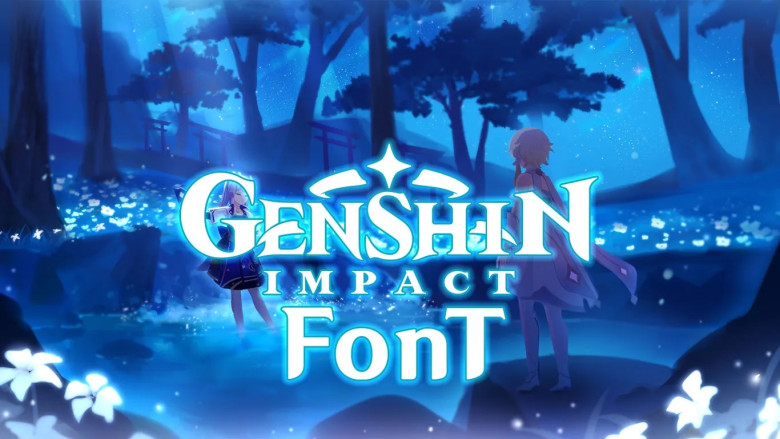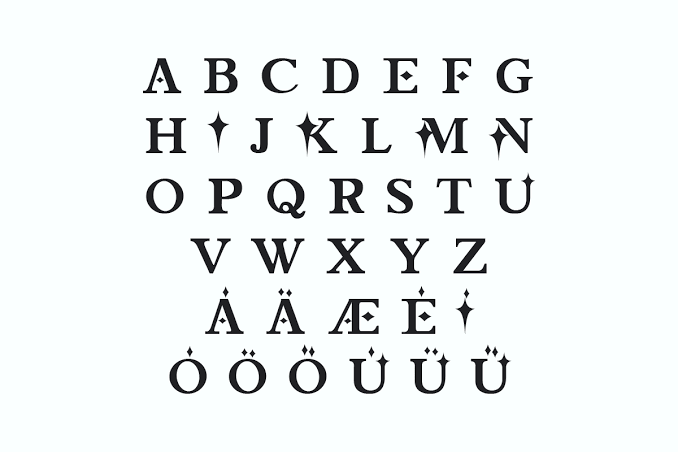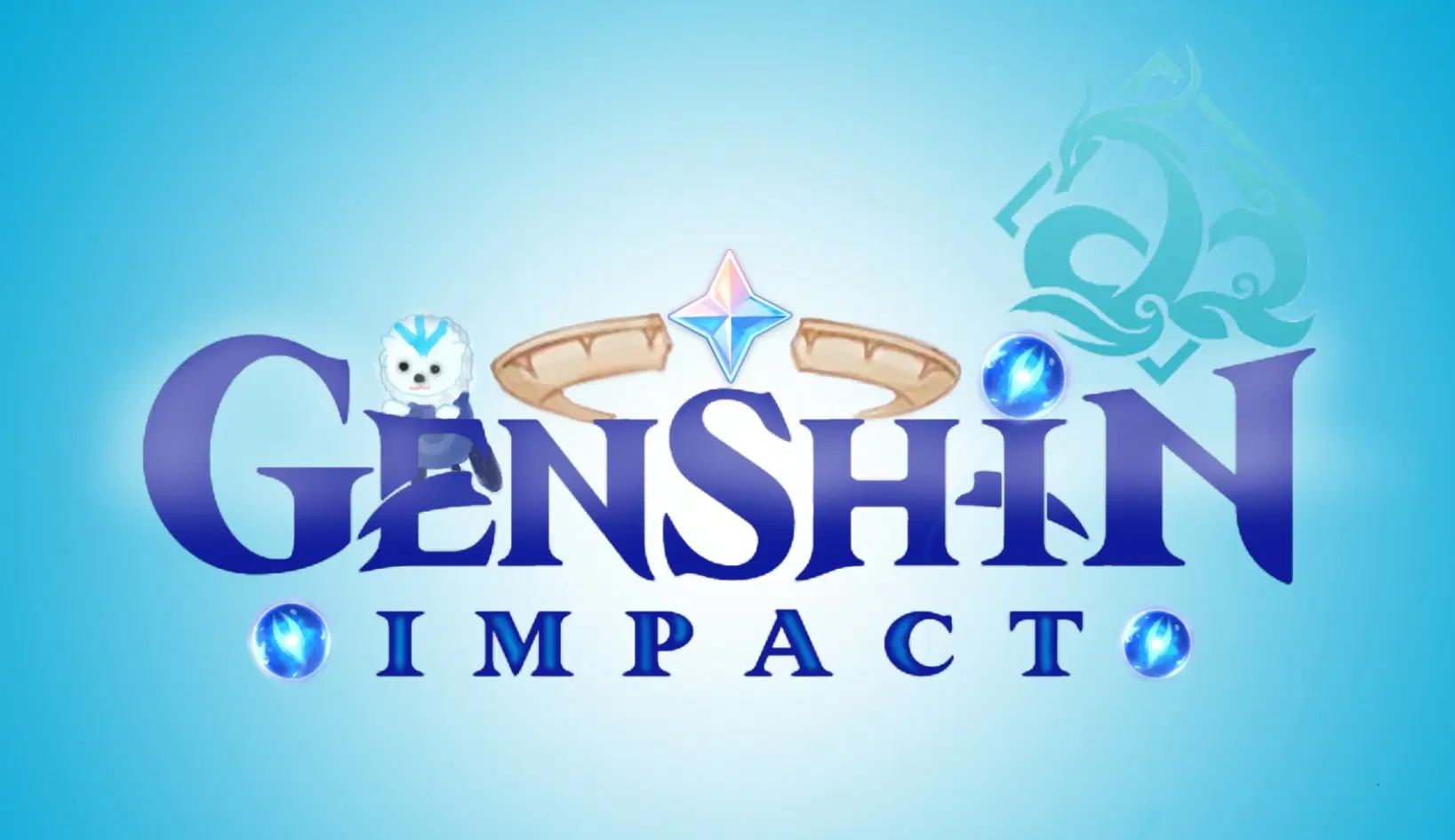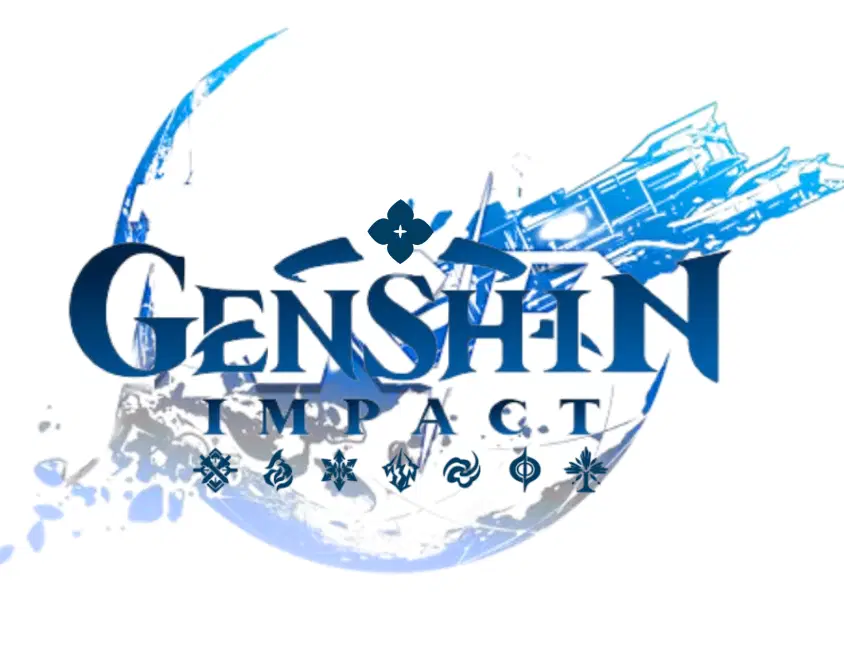
Genshin Impact Font Việt hóa là bộ phông chữ giao diện (UI) và tiêu đề chính thức được chuyển hóa từ tựa game nhập vai thế giới mở đình đám toàn cầu Genshin Impact của nhà phát triển HoYoverse. Với cấu trúc chữ không chân (Sans-serif) thanh lịch, các góc vát nhẹ nhàng mang hơi hướng huyền ảo (Fantasy RPG) và độ rõ nét xuất sắc, phông chữ này là lựa chọn số một cho các dự án thiết kế bao bì vật phẩm anime, hộp quà tặng mô hình nhân vật, poster sự kiện cosplay và ấn phẩm merchandise dành cho cộng đồng game thủ. Doozypack.vn cung cấp link tải font Genshin Impact Việt hóa chuẩn kỹ thuật, giúp bạn sở hữu phông chữ đậm chất phiêu lưu này mà không lo gặp bất kỳ lỗi hiển thị dấu thanh nào khi thiết kế in ấn.
Đặc điểm thẩm mỹ độc đáo của bộ font Genshin Impact
Genshin Impact font không phải là một phông chữ công nghệ khô cứng; nó được thiết kế tỉ mỉ để hòa quyện vào thế giới kỳ ảo Teyvat, mang lại cảm giác vừa hiện đại vừa đậm chất sử thi cổ điển.
Phong cách Fantasy RPG thanh lịch mang hơi thở Teyvat
Đặc trưng lớn nhất của Genshin Impact Font Việt hóa là sự kết hợp giữa nét chữ thẳng đứng dứt khoát và các đầu nét hơi loe nhẹ (flared terminals) tinh tế. Thiết kế này gợi liên tưởng đến những cuốn cổ thư phép thuật, bảng nhiệm vụ thám hiểm và giao diện chiến đấu sắc sảo của trò chơi. Khi đặt phông chữ này làm tiêu đề trên bao bì, sản phẩm của bạn sẽ ngay lập tức toát lên diện mạo sang trọng, huyền bí và tạo sự kết nối cảm xúc mãnh liệt với hàng triệu người hâm mộ tựa game này.
Cấu trúc chữ rõ nét, cân đối tối ưu cho giao diện và in ấn
Các ký tự của font chữ Genshin Impact tiếng Việt sở hữu tỷ lệ x-height rộng rãi cùng khoảng hở trong chữ (counter) thoáng đãng. Phông chữ này vốn được sinh ra để hiển thị mượt mà trên các màn hình điện thoại và máy tính độ phân giải cao, do đó khi đưa vào sản xuất in ấn thực tế trên bao bì giấy, từng nét chữ vẫn duy trì được độ sắc sảo tuyệt đối, không hề bị nhòe nét hay biến dạng.
Ưu điểm nổi bật của font chữ Genshin Impact tiếng Việt
Khi ứng dụng các phông chữ game quốc tế vào thị trường trong nước, sự chỉn chu về dấu câu là yếu tố quyết định đến tính chuyên nghiệp của bản thiết kế:
- Khắc phục triệt để lỗi dấu tiếng Việt: Phiên bản Việt hóa đã được đội ngũ thiết kế trau chuốt thủ công từng dấu câu. Các dấu sắc, huyền, hỏi, ngã, nặng được vẽ với tỷ lệ cân đối, đặt ở vị trí thoáng đãng so với thân chữ, không gây cảm giác chắp vá hay đè nét làm mất tính thẩm mỹ huyền ảo.
- Bảo đảm tính đồng nhất thương hiệu: Việc sử dụng bản font chuẩn giúp bạn tự tin dàn trang tên nhân vật, câu thoại hay lời chúc tiếng Việt mà không lo hiện tượng lỗi ô vuông hay nhảy về font hệ thống khô khan.
03 Ứng dụng thực tế của font Genshin Impact trong sản xuất bao bì tại Doozypack.vn
Sự huyền ảo và sang trọng của Genshin Impact mang lại hiệu ứng thị giác đắt giá trên các dòng sản phẩm bao bì thực tế do Doozypack.vn sản xuất:
- Hộp đựng mô hình nhân vật (Figures) & Quà tặng sự kiện: Tiêu đề thương hiệu in bằng font Genshin Impact kết hợp kỹ thuật ép kim nhũ vàng trên giấy Ivory cán màng mờ tạo nên vẻ đẹp sang trọng chuẩn phong cách quà tặng sưu tầm cao cấp.
- Bao bì thẻ bài (Trading Cards) & Phụ kiện công nghệ: Tên dòng sản phẩm in bằng font game tạo cảm giác hiện đại, đậm chất thể thao điện tử và khơi gợi niềm đam mê khám phá của game thủ.
- Túi giấy quà tặng Anime & Lễ hội Cosplay: Dùng cho tên cửa hàng in trên nền túi giấy tối màu mang lại phong cách huyền bí, tinh tế và khẳng định gu thẩm mỹ độc đáo.
Lưu ý kỹ thuật khi in ấn với phông chữ đồ họa game Genshin Impact
Việc sản xuất bao bì thực tế sử dụng các phông chữ game đòi hỏi sự am hiểu kỹ thuật chuyên sâu tại xưởng in Doozypack.vn: